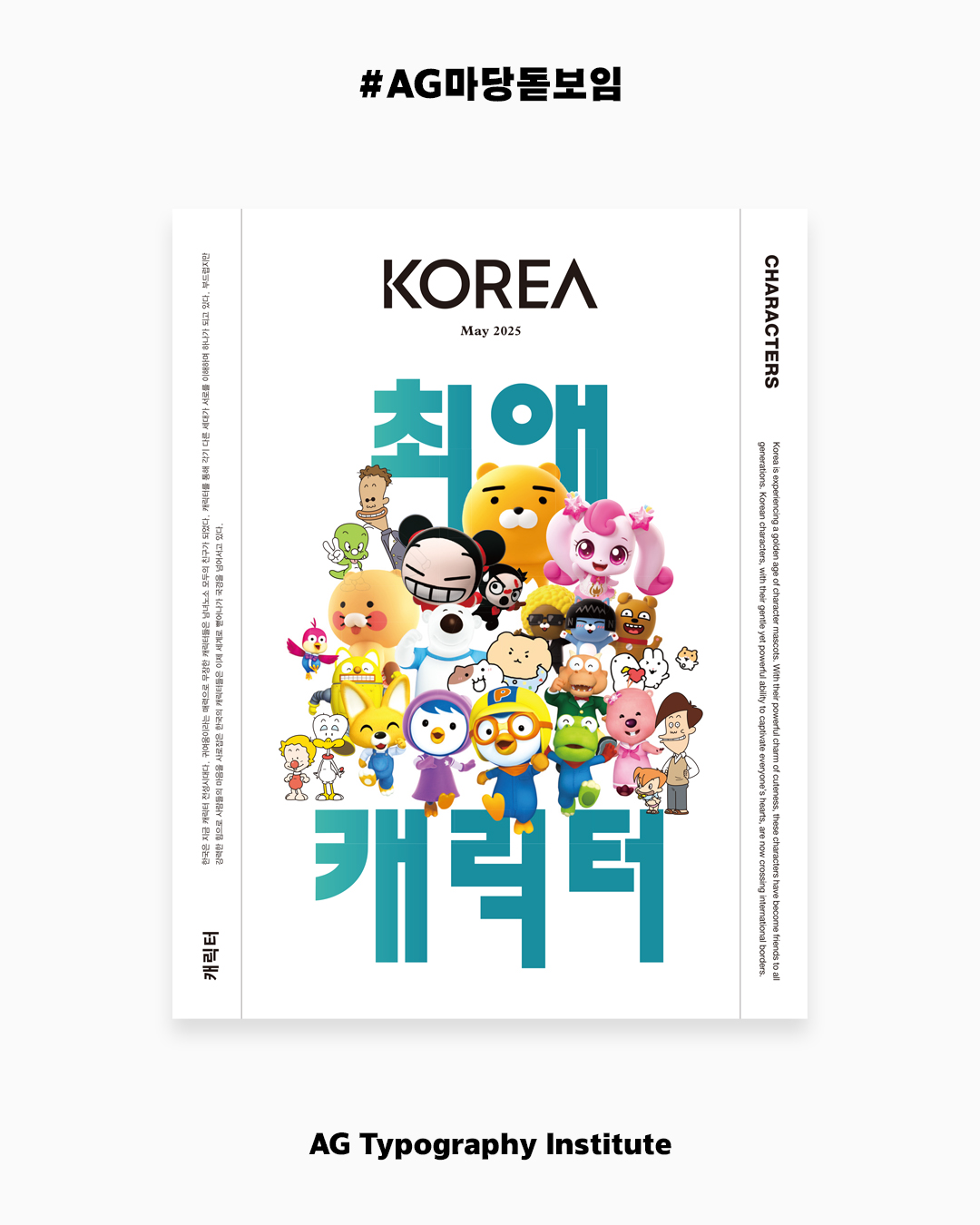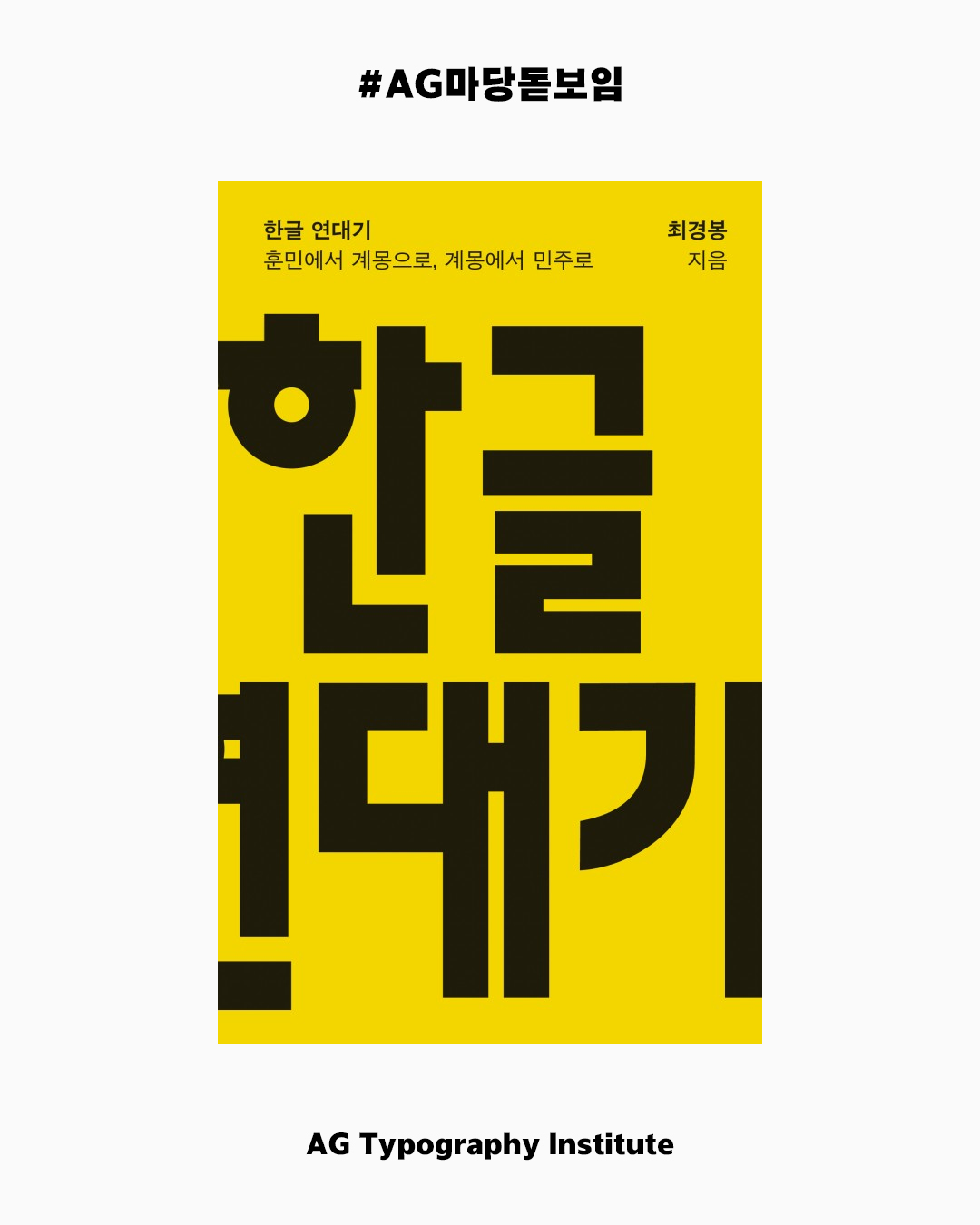
AG 마당 돋보임
AG MadangDisplay
《AG 마당 돋보임》은 연구소가 소장하고 있는 ‘마당체’ 원도, 한글 174자를 기준으로 한글 11,172자와 라틴은 한글의 특징을 담아 설계되었습니다. 원도는 디자이너 안상수가 잡지 『마당』의 아트 디텍터로 재직할 당시 그렸고, 1995년 안상수가 설계한 〈안상수체〉의 전 단계인 네모틀 조합형 글꼴입니다. 속공간이 극단적으로 작고, 글자사이도 매우 촘촘하며 닿자와 글자너비가 불규칙한 것이 특징입니다. 또한 방안지에 제도하듯 그렸기에 곡선을 최대로 배제한 기하학적 형태로 구성되어 있으며, 속공간이 극단적으로 작아 복고풍 레터링에 가깝습니다. 《AG 마당 돋보임》은 ‘마당체’ 원도의 주된 특징인 촘촘한 글자사이를 유지하였고, 첫닿자 크기를 일률적으로 맞추었습니다. 그리드를 활용하여 원도에서 나타난 불규칙한 글자너비를 9가지로 정제한 가변너비 글꼴입니다. 모든 획과 공간, 글자사이는 엄격한 그리드 규칙 내에서 움직이며 섞어짜기를 할 경우 한글, 라틴 대문자, 숫자는 윗선에 글줄흐름선이 형성되고, 라틴 소문자는 아랫선에서 글줄흐름선이 형성되는 독특한 구조를 가지고 있습니다. 《AG 마당 돋보임》은 이러한 80-90년대의 복고풍 감성에 일정한 규칙을 부여하여 현대와 어울리도록 새로운 인상을 더하였습니다.